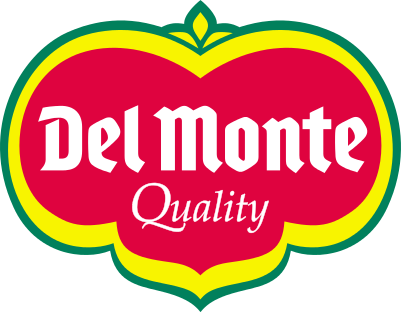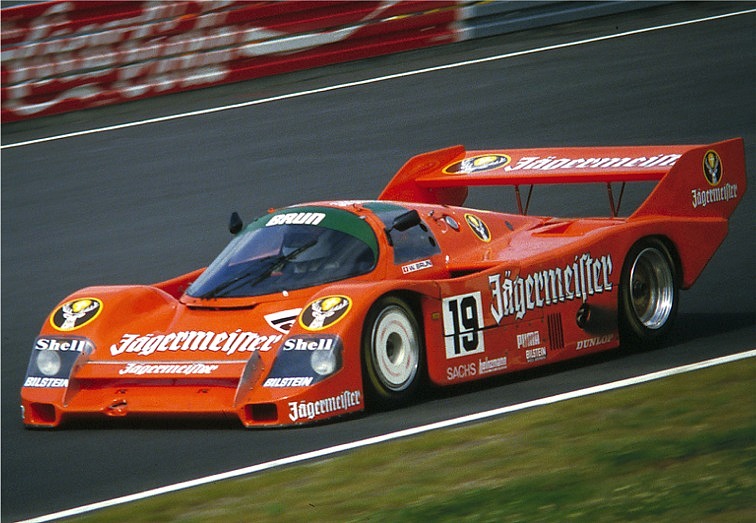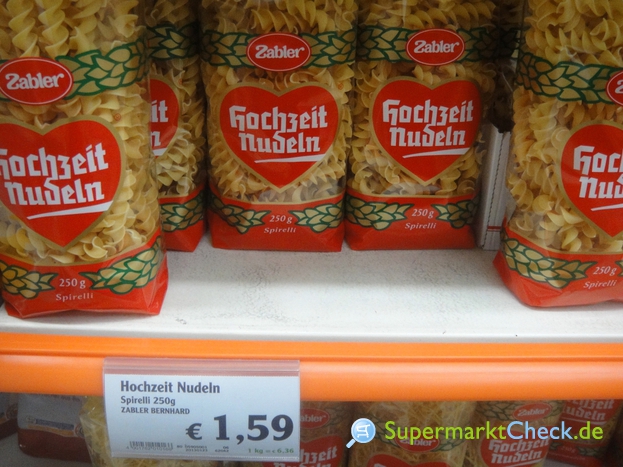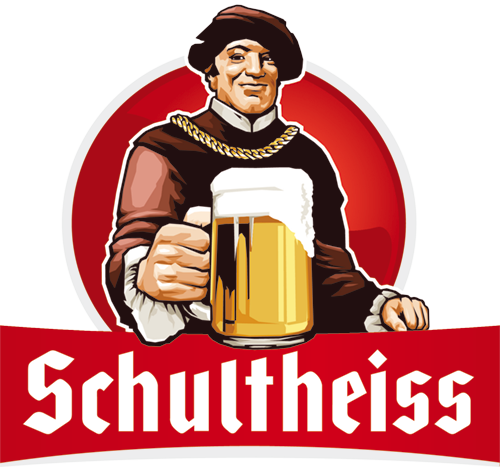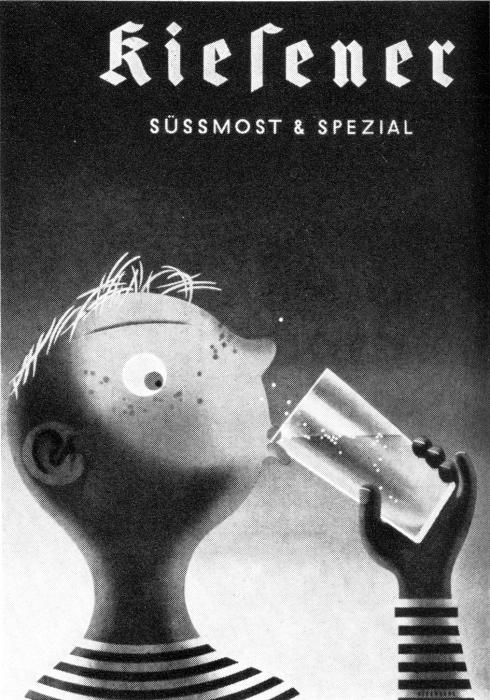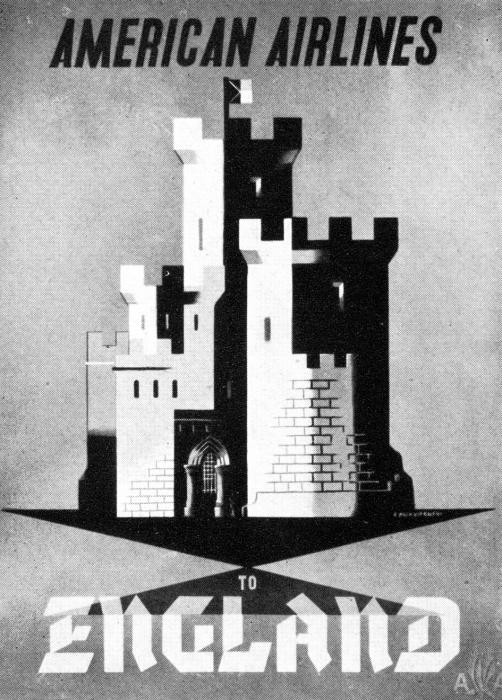
Schriftmuster Tannenberg
Nun, zunächst einmal war KdF erst einmal eine der NS-Organisationen, die es den Deutschen leicht machte, die NS-Regierung zu feiern - und damit auch dunkle Seiten in der Wahrnehmung auszublenden.
Es war ja letztlich das erste Mal, das einfache Arbeiter einen Erholungsurlaub außerhalb von Balkonien zu verschaffen. Auch wurde von KdF ja letztlich der Kreuzfahrt-Tourismus mit Schiffen wie der Wilhelm Gustloff begründet wie er heute ja durch die Aida-Flotte  fortgesetzt wird.
Auch das Deutsche Reisebüro, und damit die Firma DER hatte in den 30ern eine tiefste Verpflechtung mit KdF - und organisierte dann später auch die Reisen nach Auschwitz, inkl der Abrechnung mit der Deutschen Reichsbahn.
Was jetzt den Zusammenhang mit Tannenberg und Eisenbahn, besonders den Provinzbahnhöfen betrifft: Natürlich ist die DIN1451, mit ihrer preußischen Vorgängerschrift DIE Eisenbahnschrift, denn daher kommt sie ja.
Aber eben auch sollte in den 1930ern die Bahnhöfe im Reich deutlich mit den Ortsnamen versehen werden, und dazu war die DIN1451 zum einen einfach zu schmucklos und trotz der Einfachheit in der Größe für durchschnittliche Maler nicht wirklich einfach sauber an die Wand zu bringen, Hier boten sich die Schaftstiefler geradezu an, zum einen haben sie schon ein wenig mehr einen ornamentalen Effekt, zum anderen kann sie jeder halbwegs geübte Maler, der gerade Stiche zu Wege bringt auch sauber auf die weiß getünchte Fläche schreiben. Und da dies nicht nur sauber, sondern auch sehr dauerhaft gemacht wurde, prangt dieser Schriftzug eben noch heute an den Fassaden von hauptsächlich Provinzbahnhöfen. Und so ist das dann eben auch zur typischen Eisenbahnschrift geworden.
Nachdem es sich bei diesem einzigen (?) hier in diesem Faden gezeigten Beispiel aus dem 21. Jh. ausgerechnet um eine Speisekarte handelt, passt folgende Weisheit:
Aus einem Ferkel kann selbst der beste Koch keine koschere Delikatesse machen.
schade das du nur mit polemik antwortest, ich finde die speisekarte sehr gelungen.
wir hatten hier schonmal einen thread 'schaftstiefelgrotesk', da waren auch noch anderen beispiele drin.
auch heute gibt es noch viele biermarken die schlichte gotische schriften verwenden.
die plakate der volksbühne kennst du?
ist natürlich immer eine frage des wollens.
ich könnte im neoklassizismus auch überall 'nazibauten' sehen – mache ich aber nicht.
hier noch etwas nazi-obst, nazi-käse, nazi-bier und ein kdf-wagen ...
^ Ich spare mir, auf den polemisch vorgetragenen Vorwurf der Polemik eine polemische Rückäußerung zu erklären, stattdessen frage ich doch besser einfach: Bei welchem Deiner hiesigen Beispiele, Robert, handelt es sich tatsächlich um die in diesem Thread in Rede stehende Tannenberg
Es geht in dem Strang keineswegs speziell um die Tannenberg, sondern um die Schriftkategorie, der die Tannenberg angehört.
Fein, dann lautet meine Frage:
Welche der von Robert hier — in diesem gegenständlichen mit «Tannenberg» überschriebenen Faden, insb. in #608 oder #609 — gelieferten Beispiele gehören zur Kategorie «groteskisierte gebrochene Schriften»?
Wieso sollte es 100 % Tannenberg sein, es geht um sog. "Nazischriften".
Ich mach Dir heute ein Beispiel in 100 % Tannenberg, wenn Du das unbedingt willst – ich bin Grafiker, ich kann das.
Wenn Du die Beispiel in #610 meinst — alle? Worauf willst Du hinaus?
die nazi-nudeln wollte ich noch nachliefern.
Diese Nudeln habe ich noch nie gekauft – nicht weil ich sie Für Nazi-Nudeln halte, aber weil ich die Gestaltung (und gerade die Schrift) für unsympathisch altbacken halte. Mir scheint hier schon sehr viel Traditionismus, Konservativismus etc. mitzuschwingen ...So sehe ich das auch bei vielen Anwendungen von anderen Gebrochenen Schriften. Müssen ja nicht alles gleich Nazis sein, aber miefigen, traditionsreichen Patriotismus finde ich genauso daneben. Soll aber nicht heißen, dass es nicht anders gehen kann – man muss dann nur eben tüchtig gegensteuern ... Ist aber auch wieder nur meine Meinung und meine Wahrnehmung.
die Volksbühne bzw. Castorf spielt aber unübersehbar mit dem Nazi-Gedanken und da wird auch gern heftig provoziert
das sagt doch schon alles:
»von Mainz bis an die Memel«
hier noch mehr:
das schlägt in die gleiche Kerbe wie die APPD oder Pogorausch
zum Bier, Kneipen etc. passen die Schriften ja – da gabs vermutlich schon einige vor den 30er Jahren und somit besteht auch ein historischer Kontext
ha ha – Jägermeister ist von 1934
bei den Hochzeitsnudeln muss ich trotzdem an BDM denken ... hab die noch nie gekauft
aus welcher Kneipe ist denn die Düsseldorfer Speisekarte ?
Wieso sollte es 100 % Tannenberg sein, es geht um sog. "Nazischriften".
Ich mach Dir heute ein Beispiel in 100 % Tannenberg, wenn Du das unbedingt willst – ich bin Grafiker, ich kann das.
Wenn Du die Beispiel in #610 meinst — alle? Worauf willst Du hinaus?
Mich würde das wirklich mal brennend interessieren: Bekommt man Gestaltungsbeispiele mit der Tannenberg hin, die nicht automatisch mit dem Thema »nationalsozialistische Gestaltung« assoziiert werden? Und auch nicht mit der von Schnitzel erwähnten Altbackenheit? Kann man so etwas wie einen ganz neuen Blick auf die Schrift erzeugen? Neue Gestaltung, die die Schrift der alten Deutungshoheit entreißt?
muss aber jetzt weg in den Pott – die jüngere deutsche Geschichte ruft :P
Eine Fracmetica hätte trotz sehr ähnlicher Formensprache eine komplett andere Wirkung und man müsste für eine Nazi-Assoziation noch weitere Faktoren beitragen.
So sehe ich das z.B. auch mit Rammstein und den Leni Riefenstahl Clips – wenn man mit Olympia 1936 nicht die Nazis in Verbindung bringen möchte sieht man darin auch keine Nazi-Ästhetik
bezog sich darauf. sorry, dann hatte ich dich falsch verstanden.